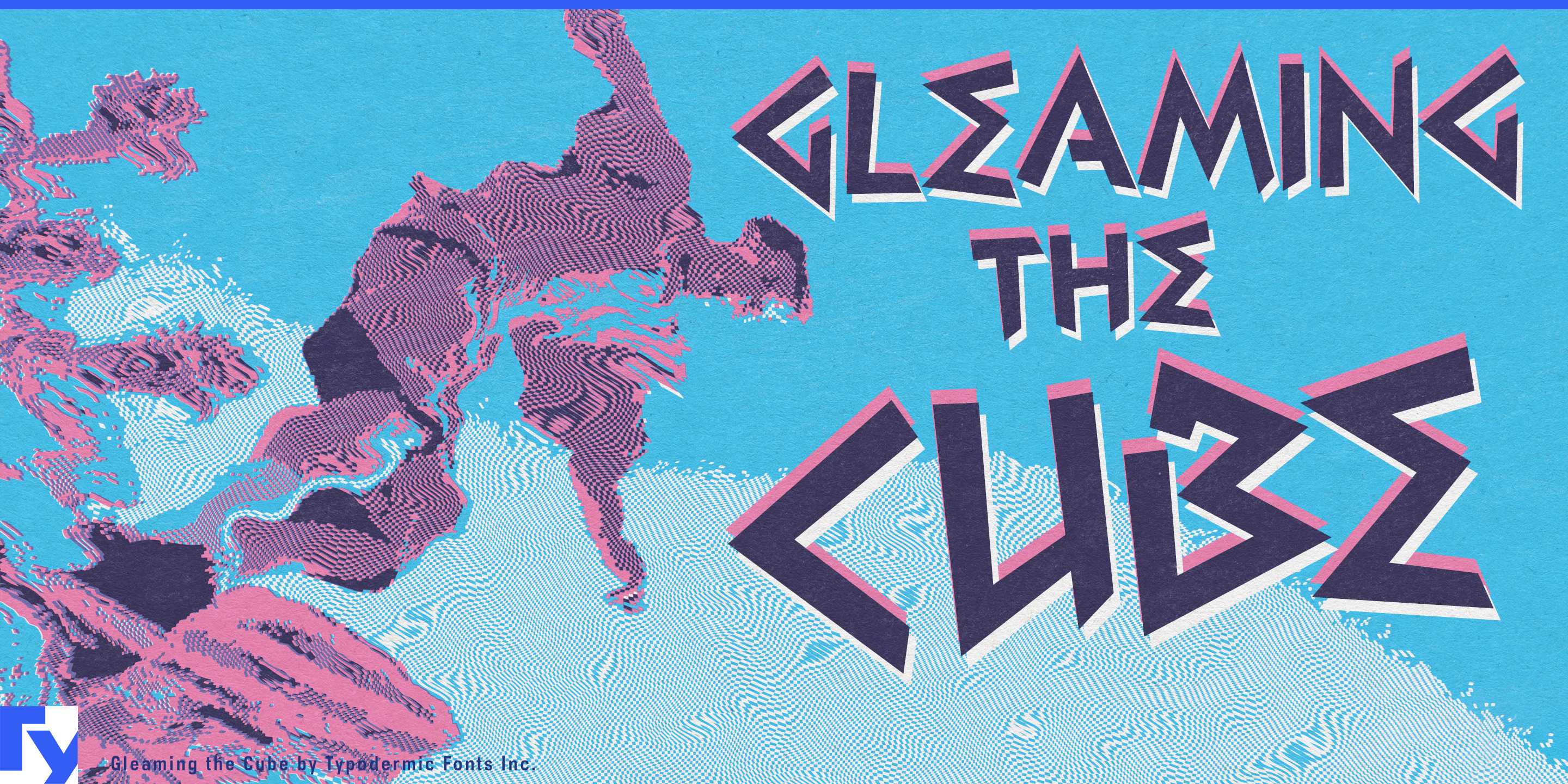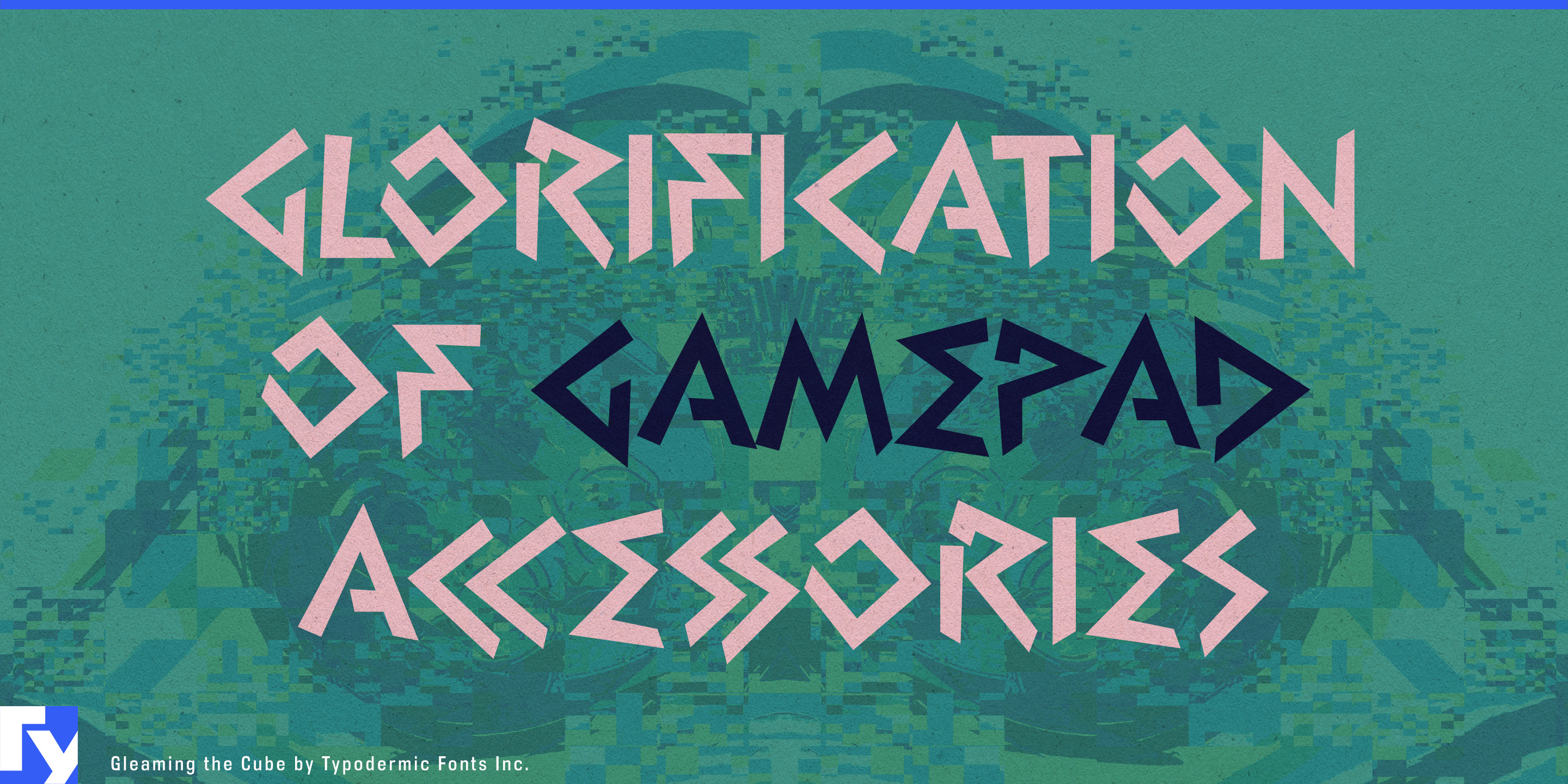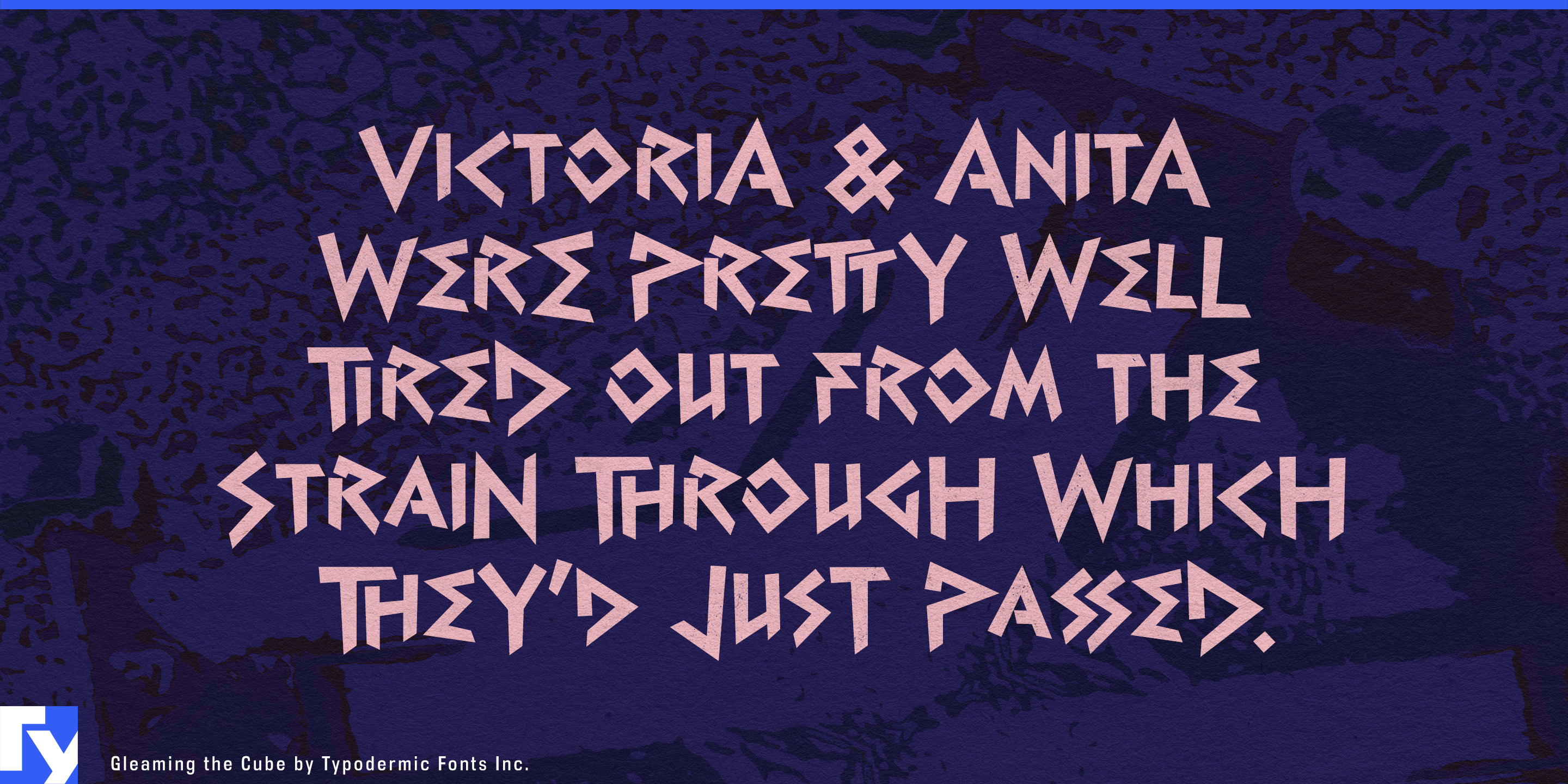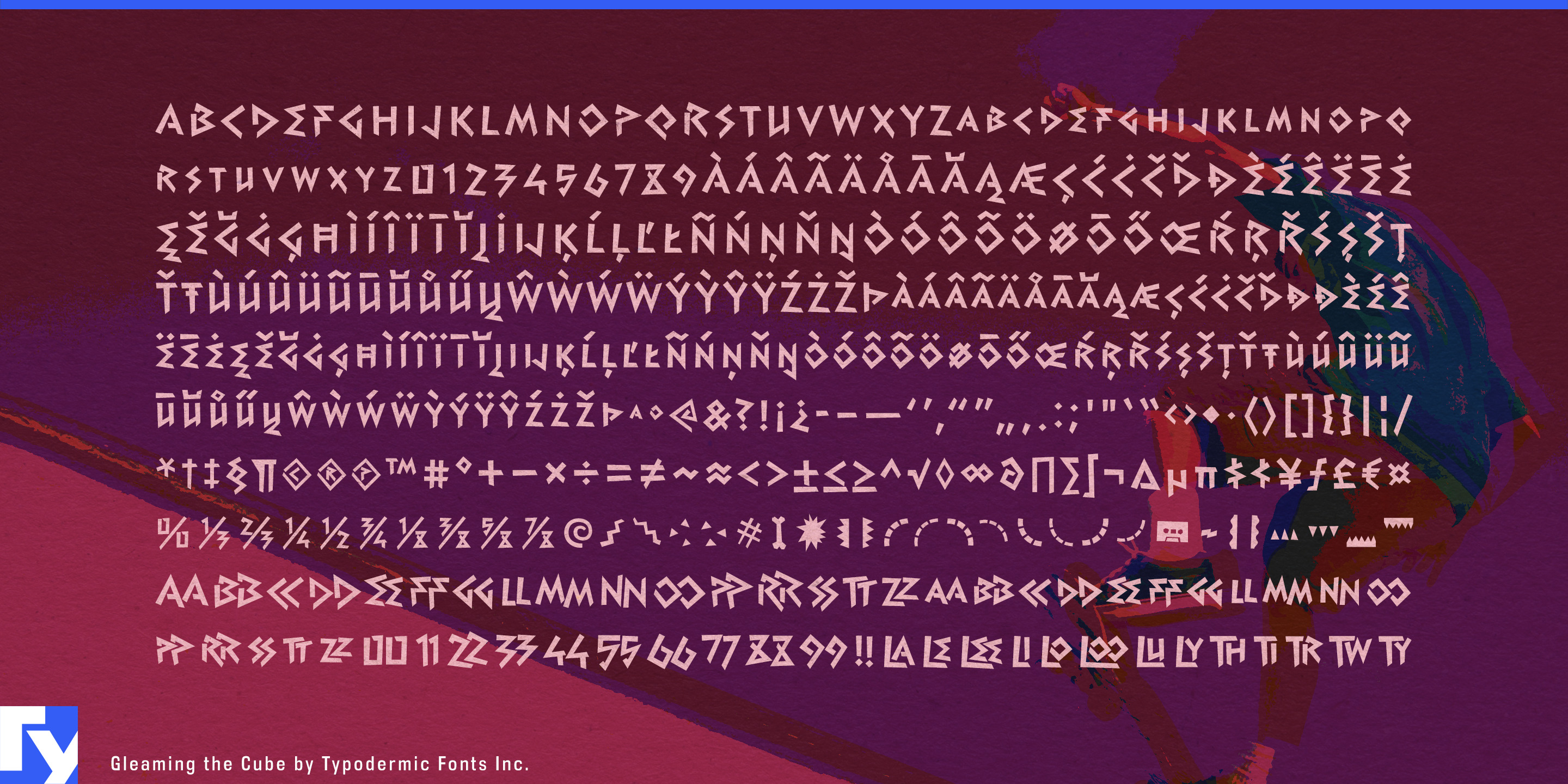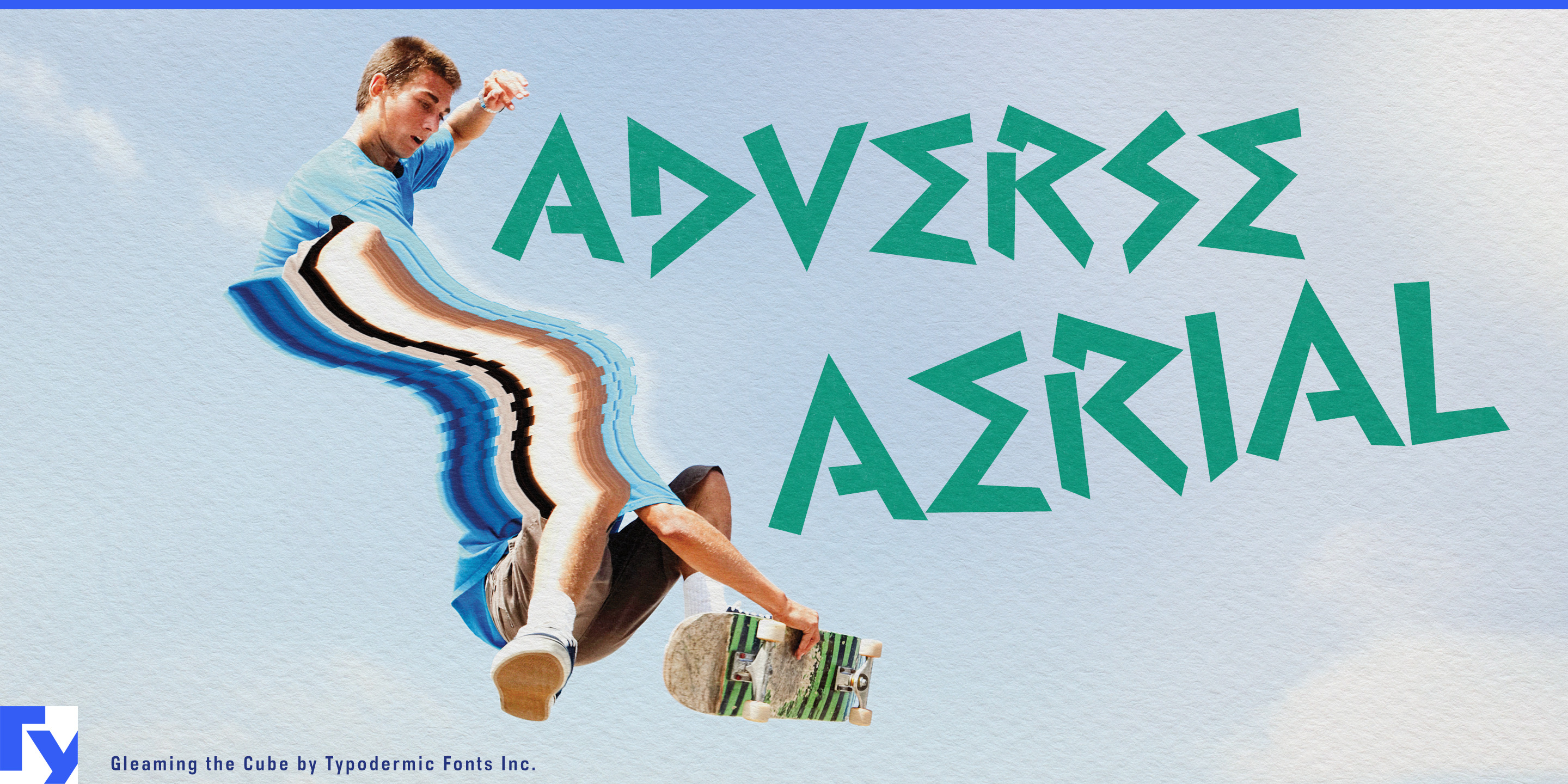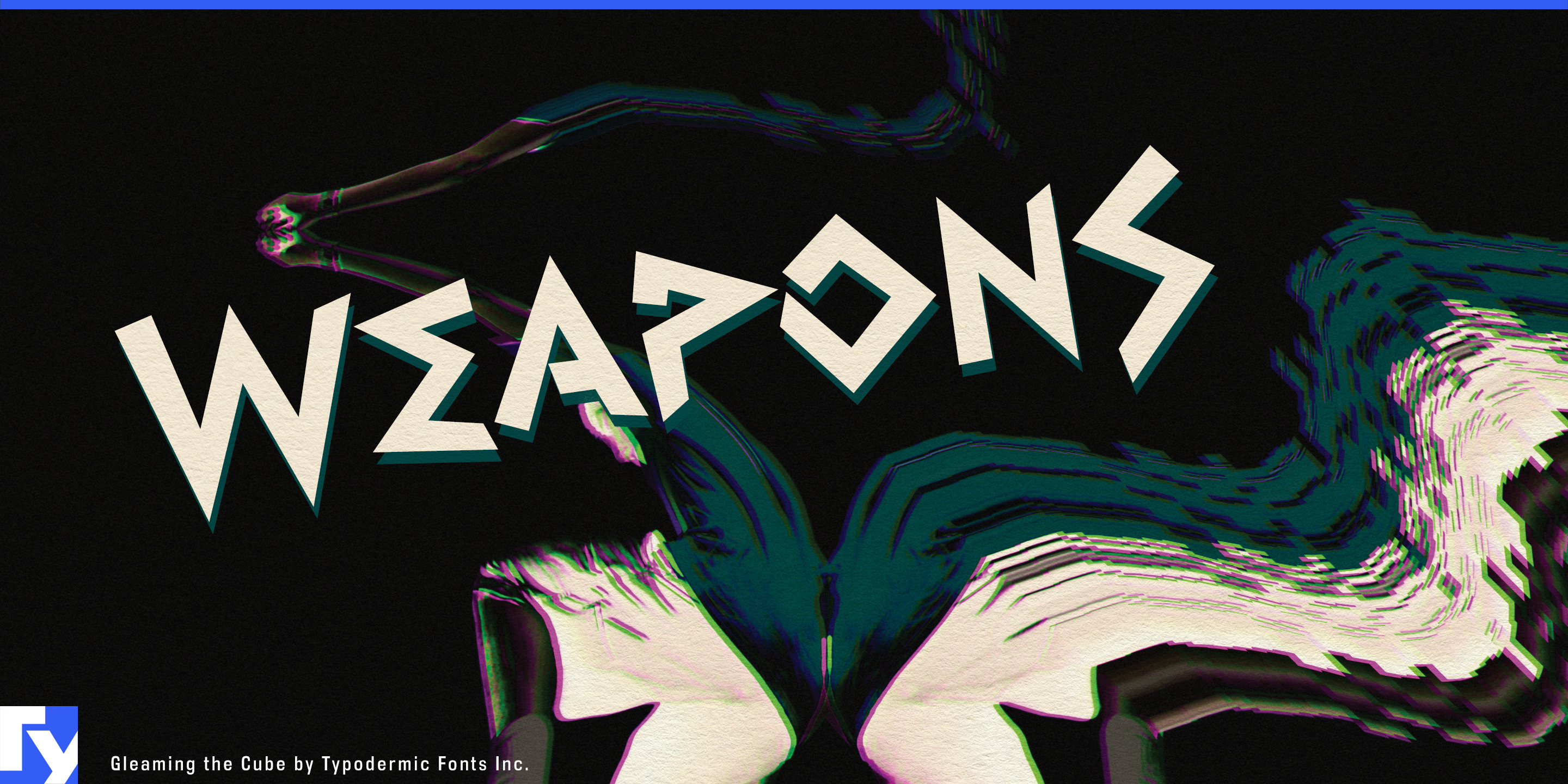
Gleaming the Cube
Actiongrafiken der späten 1980er- und frühen 1990er-Jahre lassen sich leicht auf Pixel, Chrom und Neon reduzieren. Eine andere visuelle Sprache dieser Zeit bestand aus harten Winkeln, Keilen, Zickzacklinien und abrupten Richtungswechseln. Diesen Weg schlägt Gleaming the Cube ein.
Ihre geometrischen, pseudogriechischen Buchstabenformen scheinen gegen unsichtbare Grenzen zu prallen und in neuen Winkeln weiterzuschießen. So erhalten kurze Wörter eine ausgeprägte Dynamik des Abprallens. Großbuchstaben am Anfang und Ende eines Wortes können eine kompakte, emblemartige Silhouette bilden, während Kombinationsligaturen und eigens gestaltete Symbole im Stil um 1990 weiteres Material für Displaygrafiken liefern.
Die Skate-Kultur bildet den historischen Bezugspunkt. Dadurch passt Gleaming the Cube selbstverständlich zu Boardgrafiken, Skateshop-Aufklebern, Ausrüstungsverpackungen, BMX-Startnummerntafeln und anderen Anwendungen, bei denen Schrift zum Teil des Objekts wird. Dieselbe Geometrie des Zurückprallens eröffnet im Pickleball eine überraschend zeitgemäße Richtung: Schlägerflächen, Modellnamen, Ballverpackungen, Turniergrafiken und Vereinsartikel können die abrupten Richtungswechsel der Schrift in ein visuelles Echo des Spiels verwandeln.
Die Winkel funktionieren auch erstaunlich gut bei Snacks. Saure Süßigkeiten, scharfe Chips, Kaugummi, Wassereis und Slush-Getränke bieten Keilen, Strahlenformen und Zickzacklinien einen passenden Einsatzort. Die Anmutung der Zeit um 1990 kann zugleich bei älteren Millennials und jüngeren Angehörigen der Generation X nostalgische Erinnerungen an Convenience-Stores wecken. Für kurze Produktnamen, Sortennamen, Fahrernamen und Überschriften liefert Gleaming the Cube die grafische Wirkung; kombinieren Sie sie mit einer ruhigeren serifenlosen Schrift für Zutaten, technische Daten, Zeitpläne und Begleittexte.